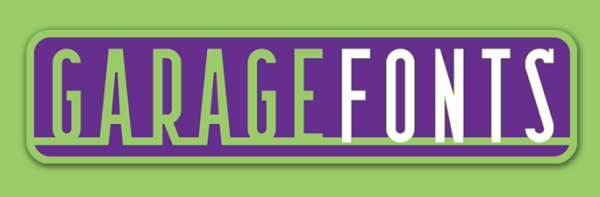
- Land: Vereinigte Staaten
- Ort: Sandy Spring, MD
- Gegründet: 1993
- Status: Anbieter ist aktiv
GarageFonts wurde 1993 als Plattform für die Schriften des Raygun-Magazins gegründet.